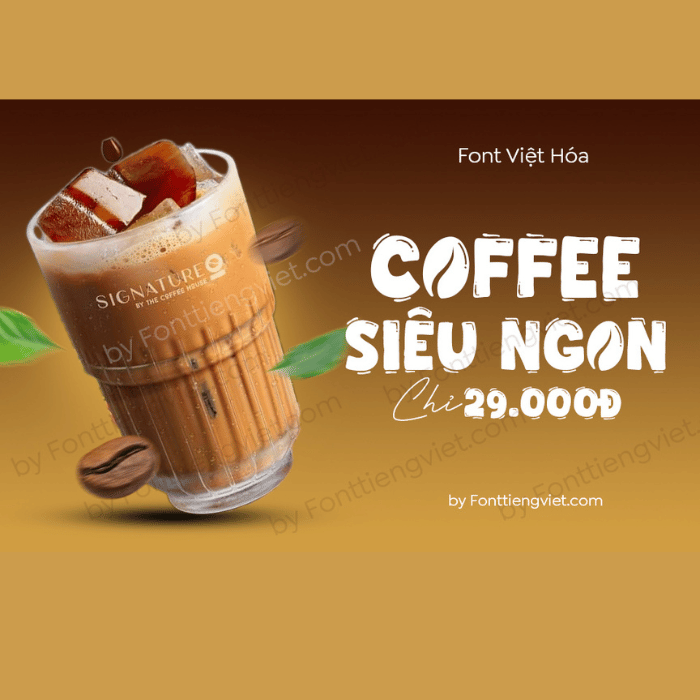
Font Việt hóa 1FTV VIP Coffee Town – Phong Cách Độc Đáo Cho Thiết Kế
Font Việt hóa 1FTV VIP Coffee Town là bộ font chữ nghệ thuật độc đáo, được thiết kế dành riêng cho dân sáng tạo. Với nét chữ mềm mại, phóng khoáng kết hợp phong cách vintage, font chữ này phù hợp với các dự án thiết kế poster, logo, menu quán cà phê, bìa sách, và nhiều ấn phẩm nghệ thuật khác.
✔ Nét chữ độc quyền – Phong cách retro, mang lại cảm giác hoài cổ, ấm áp.